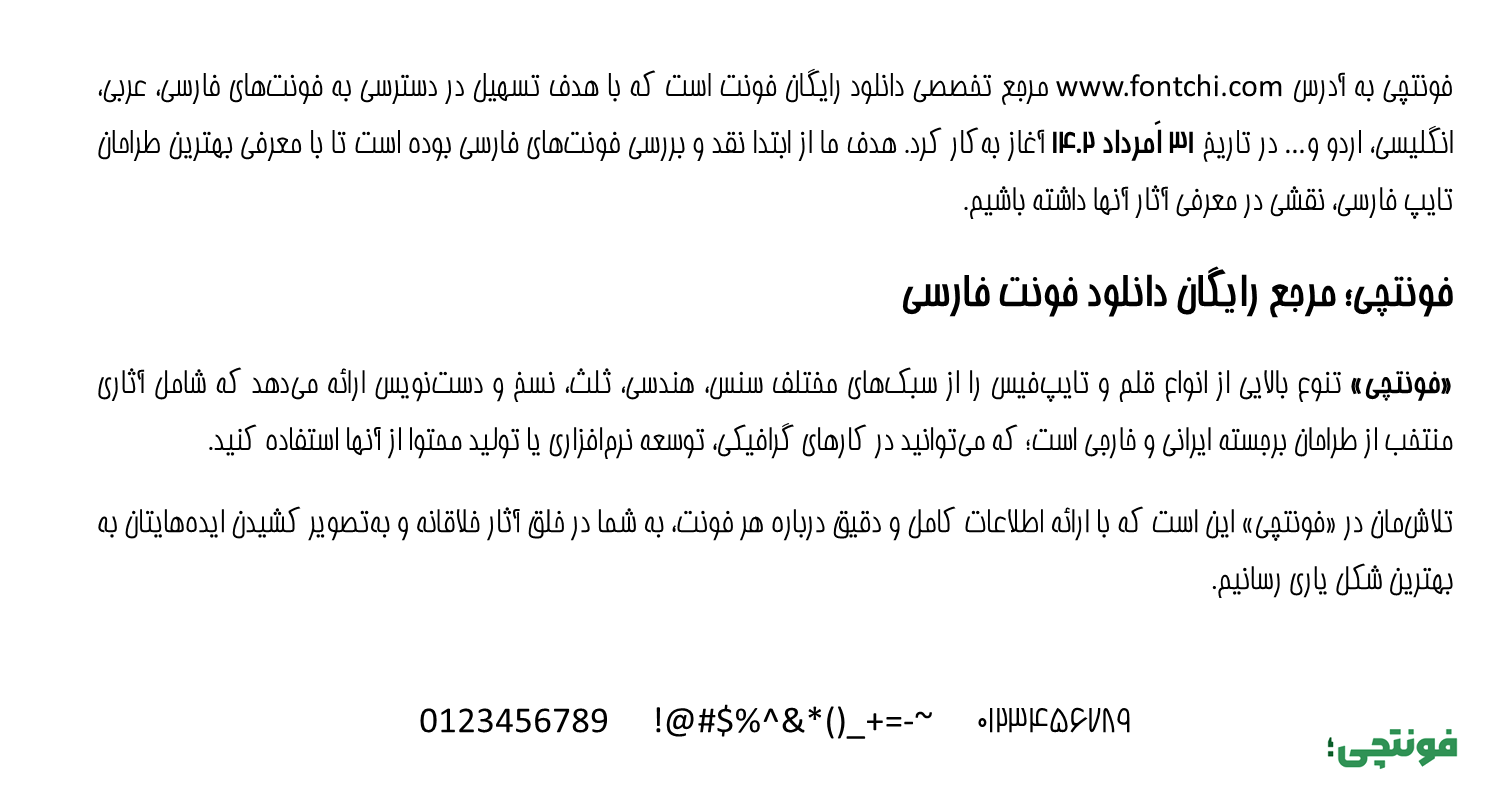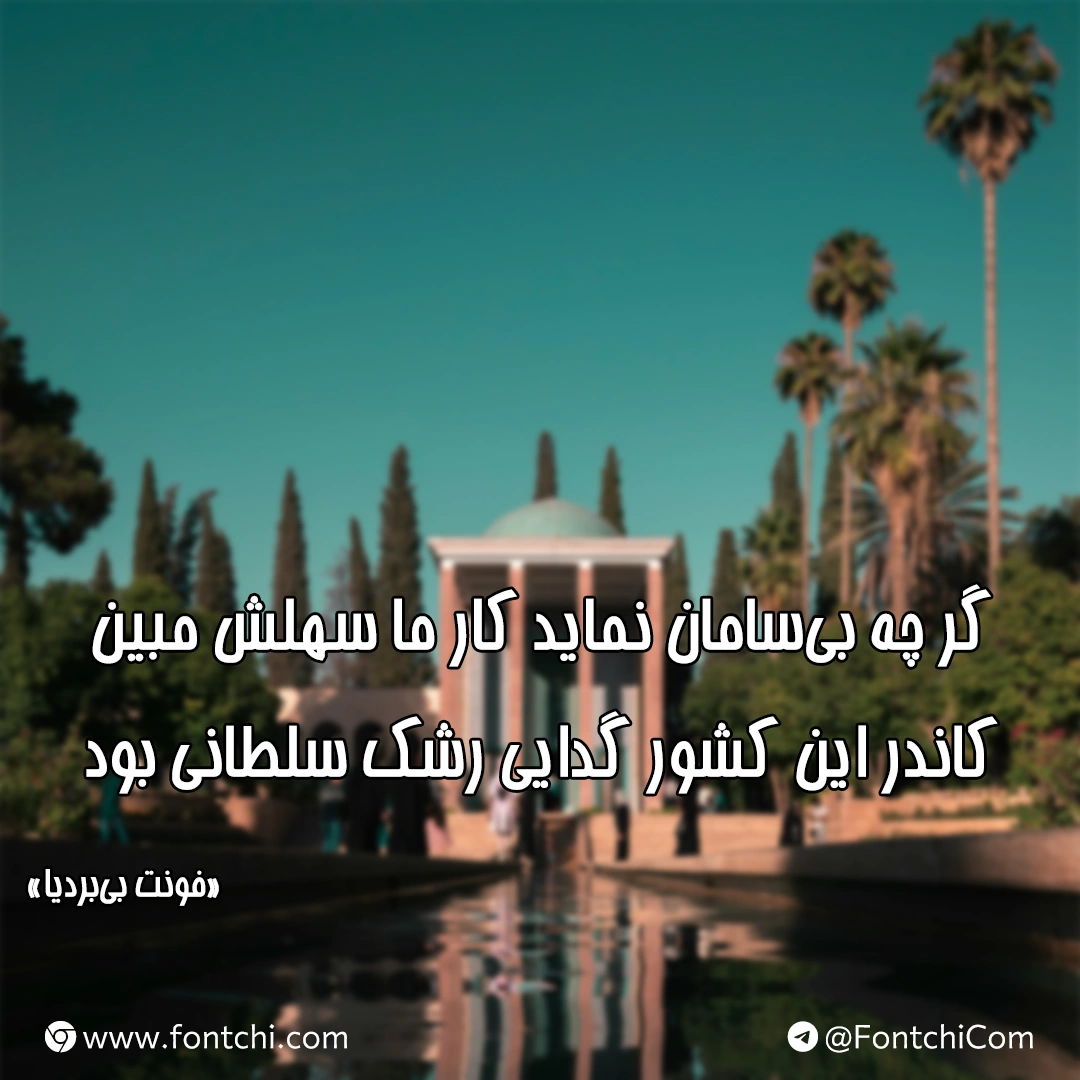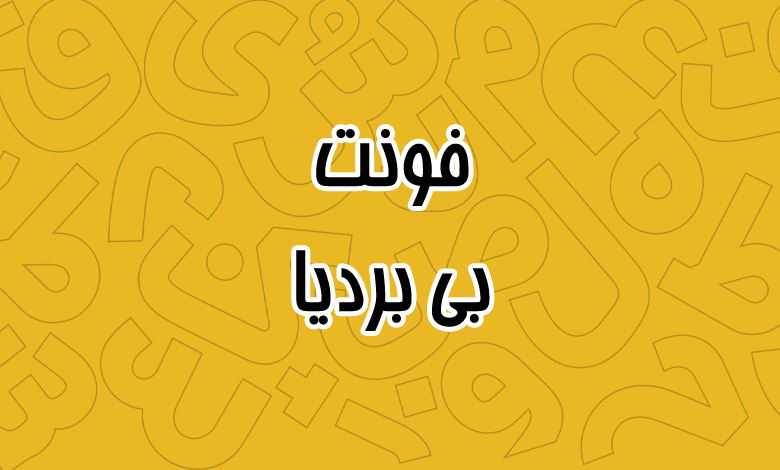
فونت بی بردیا (B Bardiya)
فونت بی بردیا یا بردیا (به انگلیسی: B Bardiya) یک تایپفیس خوانا، متوازن و مدرن است که از زبانهای فارسی و عربی پشتیبانی میکند. این فونت در دسته فونتهای هندسی قرار میگیرد که میتوانید در پروژههای گرافیکی یا صفحات وب از آن استفاده کنید. در ادامه با دانلود فونت بی بردیا همراه شما هستیم.
ساختار کلی فونت فارسی رایگان بی بردیا بر پایهی اشکال هندسی و خطوط متوازن طراحی شده است. حروف دارای انحنای نرم و خوانا هستند که باعث میشود در متون طولانی چشم را خسته نکند. وزن فونت ضخامت متعادلی دارد که باعث میشود در هر دو زمینه چاپی و دیجیتال خوانایی بالا داشته باشد.
معرفی و دانلود فونت بی بردیا رایگان (B Bardiya)
فونت فارسی بی بردیا با توجه به یکسان بودن با رسمخط عربی، از این زبان نیز پشتیبانی میکند. تمامی گلیفهای استاندارد هر دو زبان در این فونت وجود دارند و تنها کاستی این فونت عدم وجود اعداد عربی «۰۴۵۶» است. حروف متفاوت عربی مانند «ک، ی، ه، ؤ، ئ» گلیف اختصاصی این فونت را در خود دارند تا در پروژههای دوزبانه فارسی و عربی بتوان از این قلم استفاده کرد.
فونت بی بردیا برای حروف انگلیسی فاقد گلیف اختصاصی است و برای زبانهای لاتین از فونت پیشفرض سیستم عامل استفاده میشود. در چنین پروژههایی میتوانید از فونت جایگزین برای حروف لاتین استفاده کنید که در صفحه دانلود فونت انگلیسی رایگان تعدادی از آنها را معرفی کردهایم.
باتوجه به پشتیبانی این فونت از دو وزن، به خوبی برای استفاده در سرفصلها و متون بدنه مناسب است. فونت b bardiya دارای دو وزن زیر است:
- B bardiya Regular برای متون طولانی
- B bardiya Bold برای تیترها و سرفصلها
خوانایی بالا و ساختار متوازن فونت بردیا، آن را برای استفاده در مجلات و مطبوعات، بهویژه برای موضوعات سرگرمی یا کودک و نوجوان به گزینه مناسبی تبدیل کرده است. همچنین برای استفاده در بروشور، لوگوتایپ و تبلیغات نیز انتخاب خوبی است.